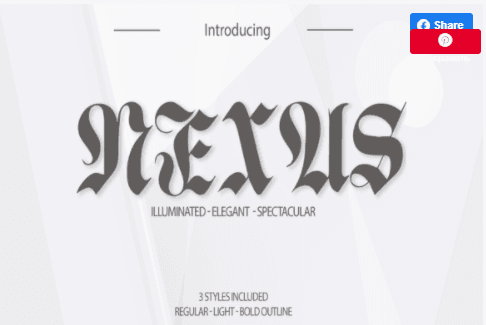
Nexus Font
Nexus - шикарный и оригинальный шрифт blackletter. Независимо от темы, этот шрифт станет невероятным активом в вашей библиотеке шрифтов, так как он может улучшить любое творение!